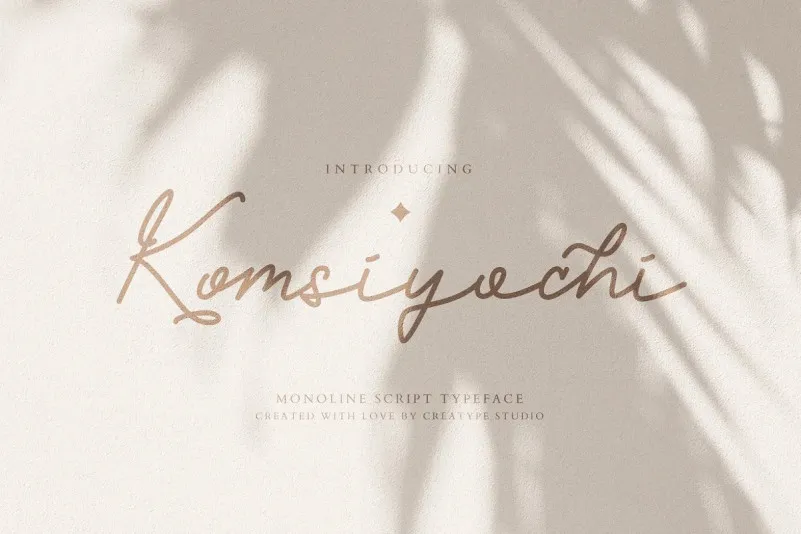
A Komsiyochi Font é uma elegante tipografia monolínea criada pelo designer Creatype Studio para várias aplicações, trazendo beleza à sua próxima criação visual. Este script foi projetado com um toque de amor e evidenciado na forma natural, suave e levemente bold que captura a essência da letra. Seja você uma designer ou simplesmente alguém interessado em adicionar charme à sua arte digital, Komsiyochi é o tipo perfeito para aqueles momentos onde um design elegante pode transformar qualquer projeto. Com seu traço fluido e delicado, esta fonte ajuda a criar designs de alta qualidade que encantam seus olhos e coração. Sua versão em script é uma escolha inspiradora para quem busca uma harmonia entre o tradicionalismo dos estilos monolíneos e a modernidade da escrita contínua.